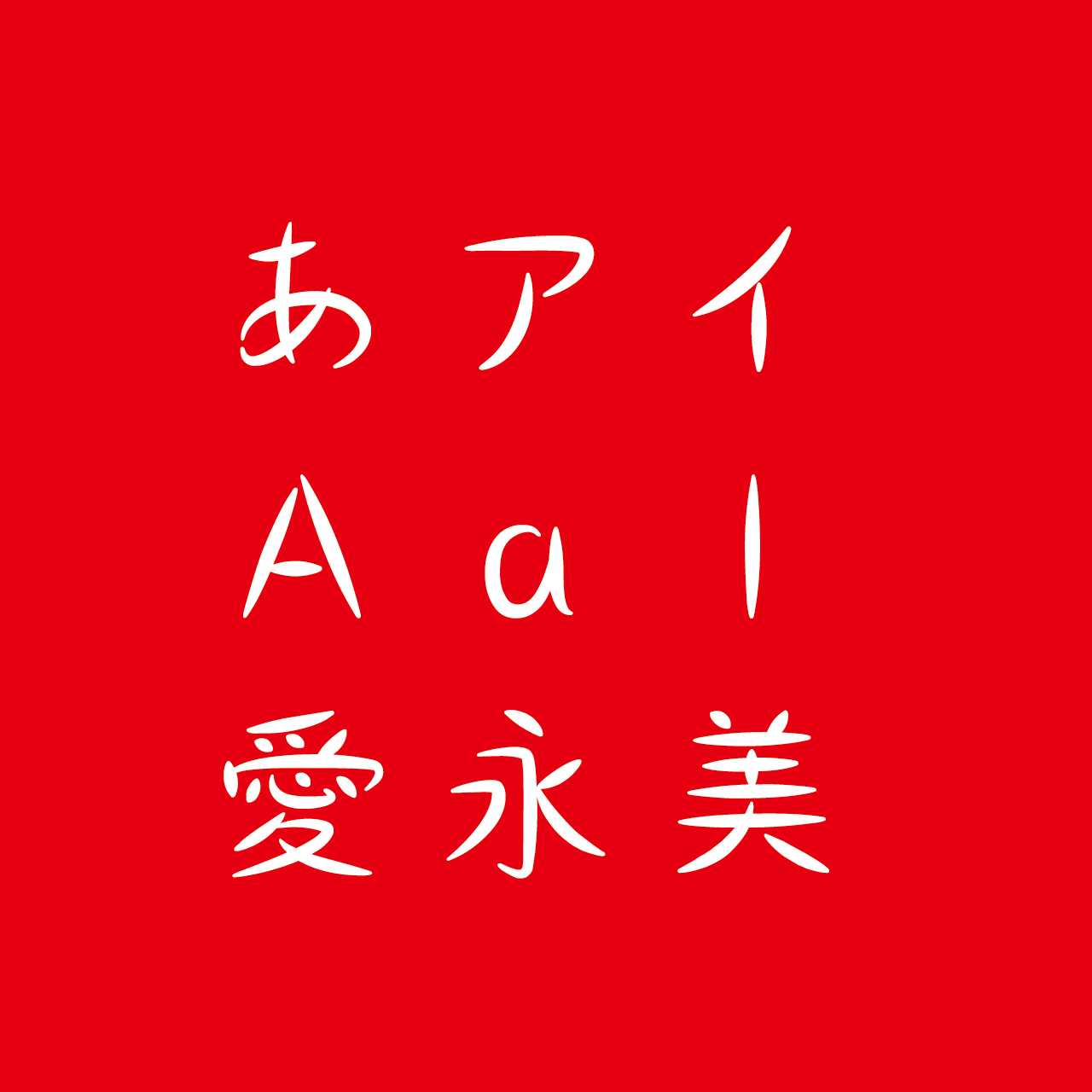
MotoyaAnemone
About "MotoyaAnemone"
MotoyaAnemone는 담담함과 덧없음을 표현한 폰트입니다.
'아네모네'는 '덧없는 사랑'이라는 꽃말을 지닌 지중해 연안에 자생하는 미나리아재비과의 꽃으로, 글자의 표정에서 금방이라도 사라질 것 같은 덧없고 옅은 이미지를 표현하고 있습니다.
웨이트 전개는 굵어질수록 점점 눈물이 흘러내리는 듯한 이미지로, 문장에 따라 슬프고 애틋한 감정을 표현할 수 있습니다.
• MotoyaAnemone W1
W1
MotoyaAnemone W1 W1
• MotoyaAnemone W3
W3
MotoyaAnemone W3 W3
MotoyaAnemone